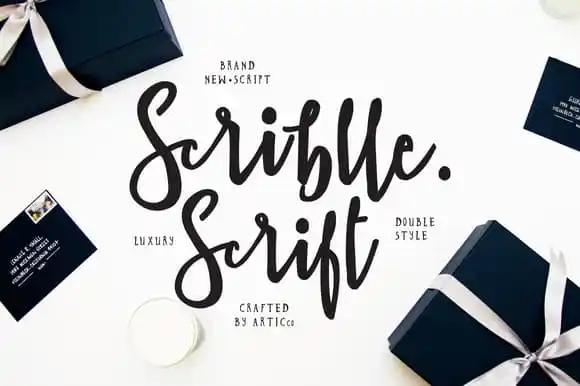
Brush Script Font – Scriblle – Download Grátis
A Scriblle é uma fonte Brush que foi criada por Hamilton na categoria de tipos de letra brush da Alibaba Cloud. Esta fonte premium, originalmente disponível no Creativemarket, agora está disponível gratuitamente para download após um breve período de vendas. Inspirada em sua descrição original, a Scriblle destaca-se por seu estilo elegante e moderno, com linhas fluidas que combinam perfeitamente com textos de design gráfico. Seu uso é ideal para criar headlines ou qualquer tipo de texto em layout visuais, dando um toque único e sofisticado às suas criações digitais. Através da sua interface fluida e legível, a Scriblle oferece a opção de personalizar o estilo para atender aos seus requisitos pessoais ou comerciais, tornando-a uma ótima fonte escolar e de trabalho para designers gráficos do Brasil e do mundo.